输入名字,挑一个样式,下载 PNG。就这么简单,大约十秒钟。
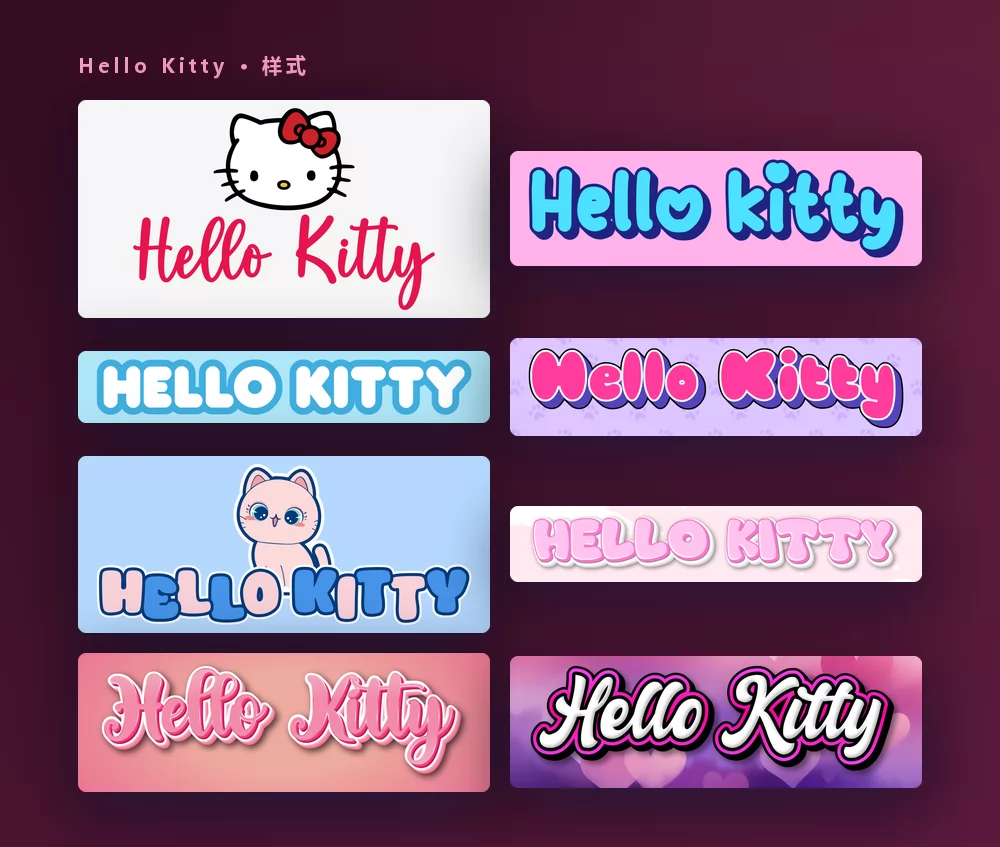
这些都来自同一个 Hello Kitty 字体生成器,只是从列表里换了个样式。无需安装,无需账号。
关于 Hello Kitty 字体
Hello Kitty 是三丽鸥旗下的日本角色,1974 年由设计师清水侑子创作,1980 年起由山口裕子负责绘制。一只左耳系着红色蝴蝶结、看不见嘴巴的白色小猫,1975 年首次出现在一个乙烯基零钱包上,之后成了全球被授权最多的角色之一,出现在玩具、文具、服装和几乎所有东西上。
这些年标志用过好几种字样,没有一种作为字体发布过:它们都是为三丽鸥绘制的定制字样。所以"Hello Kitty 字体"对不同的人意味着不同的东西,字体网站列出的也都是相似字体,而不是唯一答案。每份清单上都会出现的名字有 Janda Happy Day、Boldins、Odin Rounded、Jam Sessions、Hello Heartache 和 LMS Hello Kitty Hello。
下载任何东西之前要知道一点:下载量最高的"Hello Kitty"字体,DaFont 上 Woodcutter 那款、一百五十万次下载的,是一款符号字体。每个按键打出来的是一个小小的 Kitty 图案,而不是字母。很可爱,但写不出名字。
怎样做 Hello Kitty 文字
第一步:输入名字
打开生成器,把示例文字换成你自己的:孩子的名字、"生日快乐"、手机壁纸上的一个词。字母会随着输入实时重绘,就在 Kitty 的脸蛋下方。请保持首字母大写、其余小写:标志风格是手写体,全部大写会丢掉让它看起来像手写的连笔。
第二步:挑一个样式
经典款是浅灰底上、白色脸蛋下方的红色手写体。在"样式"选项卡里,填充、描边和阴影可以分别调整,所以你可以保留字形,把颜色换到别处:柔和的粉色、玉桂狗派对用的粉蓝色、爱心上的白色。
第三步:选好尺寸
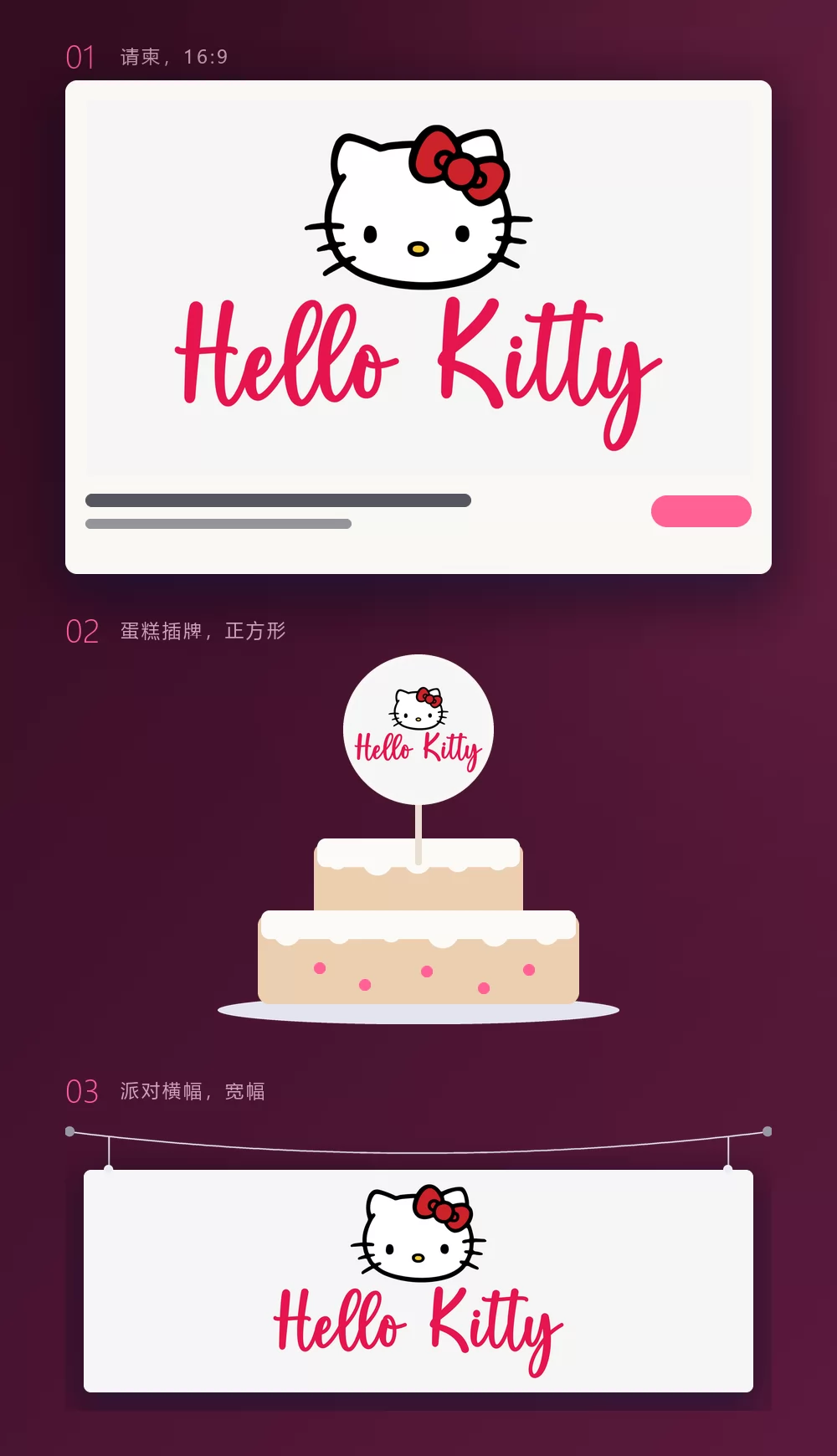
导出前先设好尺寸,之后就不用再裁。请柬用 16:9,蛋糕插牌或贴纸用正方形,挂在墙上的横幅用宽条。上面三个情景模拟,就是这些尺寸打印出来之后的样子。
第四步:下载
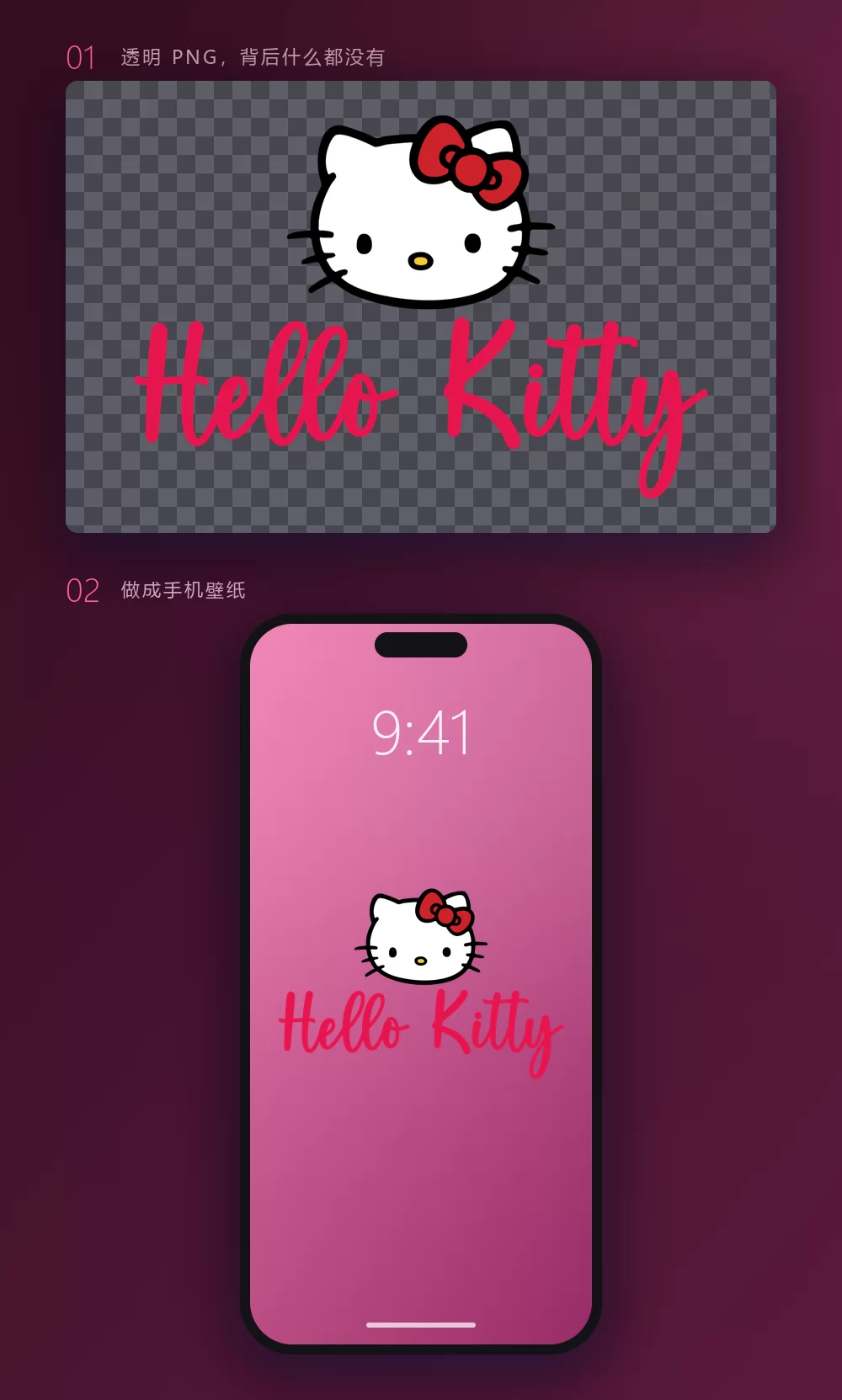
如果打算把名字放到自己的设计上,就在"下载"选项卡里选透明 PNG。这是大多数人错过的选项,而对壁纸、贴纸或打印品来说恰恰是最要紧的:你自己的背景,Kitty 和名字在上面,周围没有灰色方框。
名字一长,宽度很快就满了
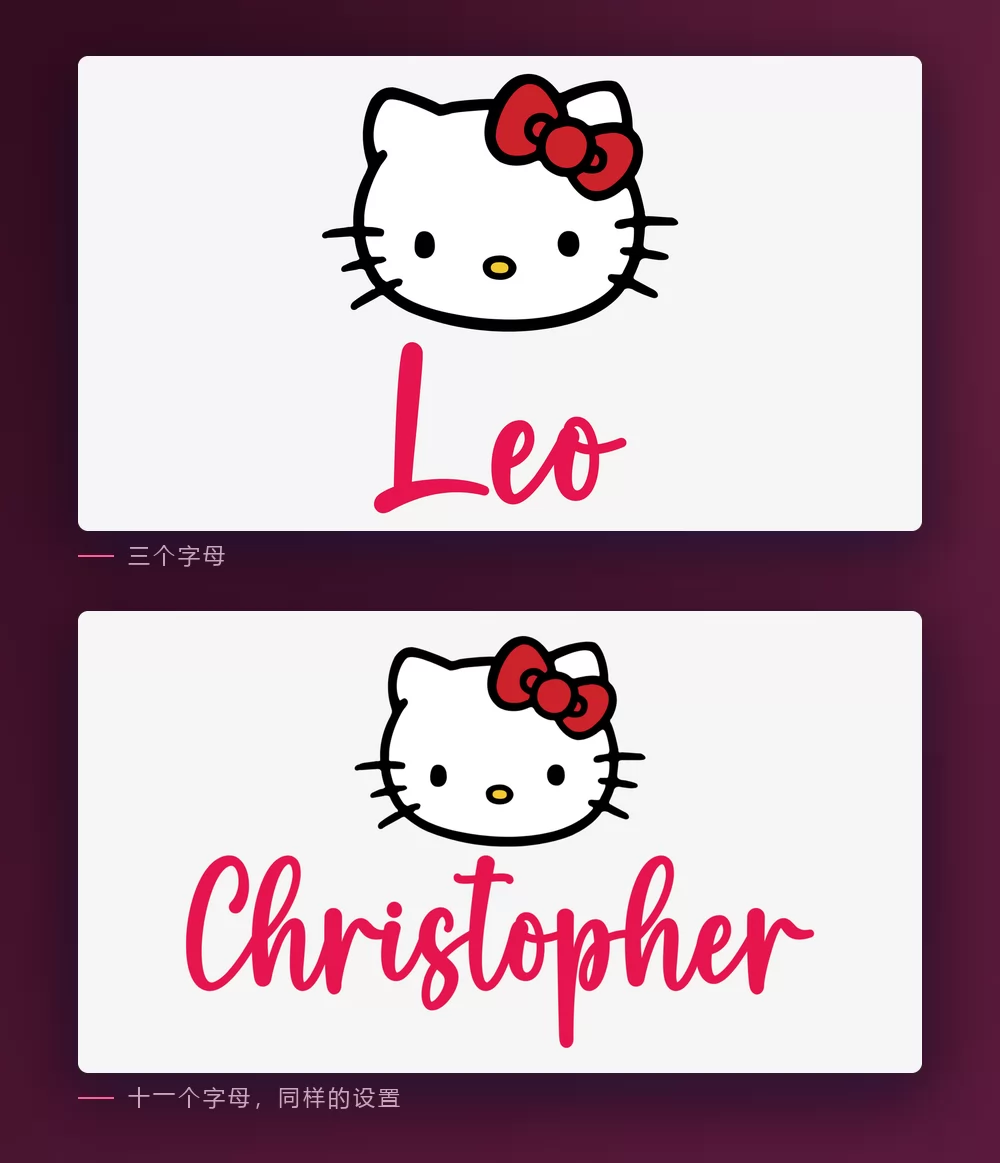
字母越多,排得越紧。字间距是"文字"选项卡里的滑块:稍微拉开一点,长名字就不再显得局促。同一个选项卡里还有缩放、行高、弧度和旋转。
Hello Kitty 风格,还是卡哇伊风格
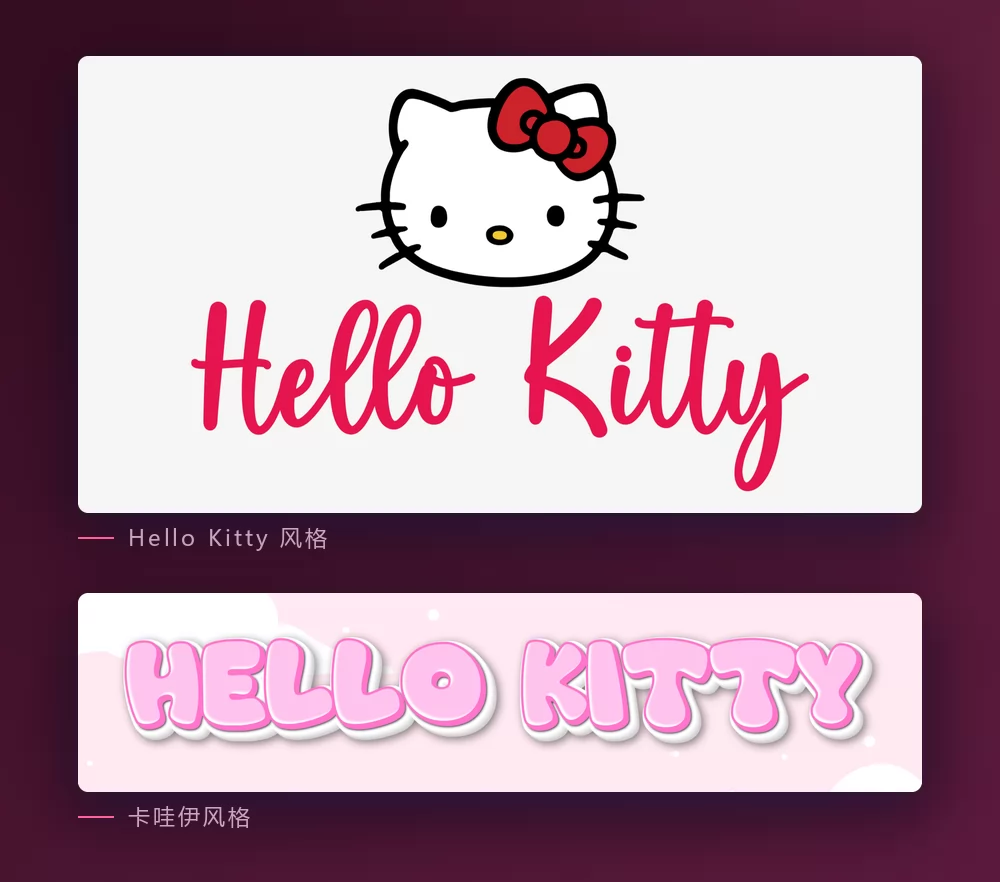
Hello Kitty 风格就是标志本身:系着红色蝴蝶结的白色脸蛋,下方是红色手写体的名字。大多数人想到的就是它,任何要一眼就看出是 Hello Kitty 的东西,都该用它。
卡哇伊风格是粉彩云朵上的粉色泡泡字母,没有任何角色。它不带三丽鸥的任何标识,所以更适合手账、店铺招牌,或者只是想可爱一点的手机壁纸。卡哇伊文字生成器里有现成的预设。
想安装字体的话,选哪一款
标志本身不是字体。它是为三丽鸥绘制的定制字样,所以任何叫"Hello Kitty 字体"的文件,都是别人对它的再现,或者只是碰巧长得像的字体。
Janda Happy Day,Kimberly Geswein 所作,是大多数清单排在第一位的:一款圆润活泼的手写体,读起来像标志。它在 DaFont 上标注为个人使用免费,下载量超过八十万次。
Odin Rounded 是授权干净的免费字体:一款简洁的圆角无衬线体,在 DaFont 上标注为 100% 免费,下载量超过五十万次。它给你标志那种柔和圆润的感觉,只是少了那份跳跃。
Boldins 是另一款常被提到的个人使用手写体,而 LMS Hello Kitty Hello 从 2001 年起就在 FontSpace 上,下载量超过一百万次,是仅限非商业用途的免费软件。把它们用到售卖的东西上之前,先读一读 readme。
做客户项目、授权必须干净时,老实的选择是 Google Fonts 上开放授权的圆体:Comfortaa,一款几何圆角字体,最接近标志的字样;以及 Fredoka,更活泼,粗细齐全。两款都不是 Hello Kitty 字体,但都能给你柔和圆润的感觉,授权没人能挑刺,而且在 Canva 里就能用。
大家真正用它做什么
这个生成器被用在 Hello Kitty 一直以来赖以生存的那些东西上:生日请柬和蛋糕插牌、手账或笔记本电脑上的贴纸、手机壁纸、名牌、派对横幅,偶尔还有店铺招牌。几乎都用透明 PNG 比装字体效果好,因为这个效果是脸蛋和红色手写体合在一起,而字体文件只给你字母,别的什么都没有。
怎样在 Canva 里做 Hello Kitty 文字
Canva 没有 Janda Happy Day,它字体库里也没有哪款自带脸蛋。但它有 Comfortaa 和 Fredoka,所以不用离开 Canva 也能得到圆润的感觉。要标志的效果,就把字样做成透明 PNG 再上传:它能直接放进 Canva 的请柬或故事里,而且依然清晰。
怎样在 Photoshop 里做 Hello Kitty 文字
安装 Janda Happy Day 或 Comfortaa,以首字母大写输入名字,然后把效果控制到最少:
- 颜色叠加,用蝴蝶结的红色,偏暖的红而不是粉。
- 不要描边,不要阴影:标志是平面的。
- 一层浅灰或白色背景,上方放角色图案,图案得你自己去找。
字母是容易的那一半。没有脸蛋,它看起来就是一行红色手写体,而不是 Hello Kitty。
怎样在 Word 里做 Hello Kitty 文字
安装字体,以首字母大写输入名字,把字母设成红色。标志需要的就这些,Word 做得到。凡是要打印或分享的东西,带脸蛋的导出 PNG 还是会更好看。
在手机上
在 iOS 和 Android 上,大多数应用都无法安装并使用字体。生成器在手机浏览器里就能运行:在手机上做好 PNG,存进相册,设为壁纸或添加到你正在用的应用里。
Hello Kitty 字体免费吗
常见问题
Hello Kitty 标志用的是什么字体? 没有字体。标志用过好几种为三丽鸥绘制的定制字样,没有一种作为字体发布过。Janda Happy Day 是大多数清单排在第一位的相似字体。
为什么 DaFont 上的 Hello Kitty 字体只能打出图案? 因为它是符号字体:每个按键都是一个 Kitty 图案。它不是一套字母。
我能用它做 Hello Kitty 蛋糕插牌吗? 能。选正方形尺寸,下载透明 PNG,打印后沿脸蛋和名字的轮廓剪下,或者把 PNG 发给切割机。
做壁纸时怎样得到透明背景? 在"下载"选项卡里选透明 PNG,然后把 Kitty 和名字放到你自己的照片或渐变上。
为什么我的文字和真正的标志比起来不对劲? 通常是少了脸蛋,不是字体的问题。单独的红色手写体只是一行红色手写体。上方加上白色脸蛋和红色蝴蝶结,哪怕换一款字体,它也像 Hello Kitty。